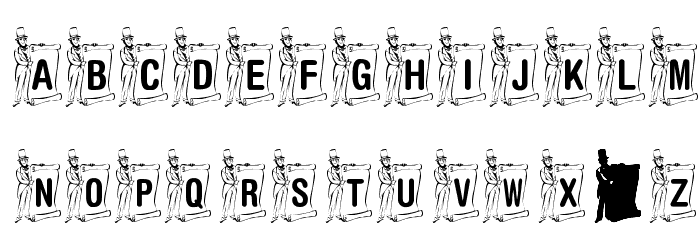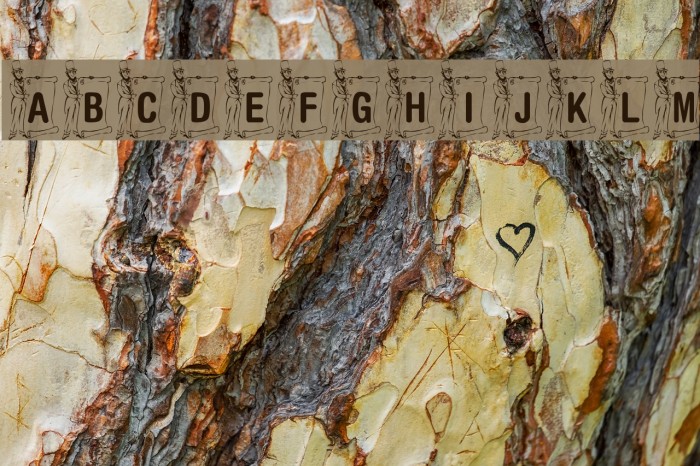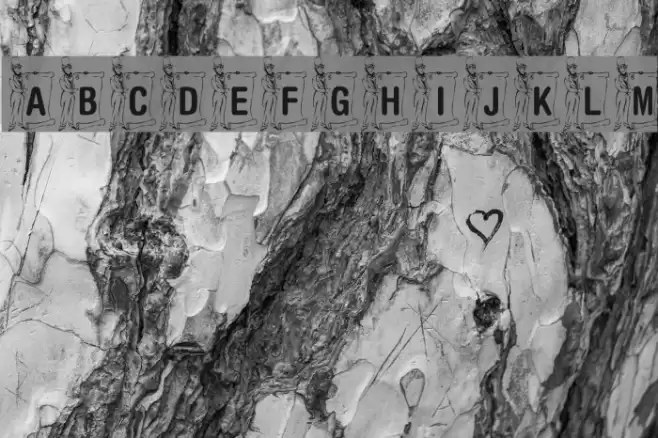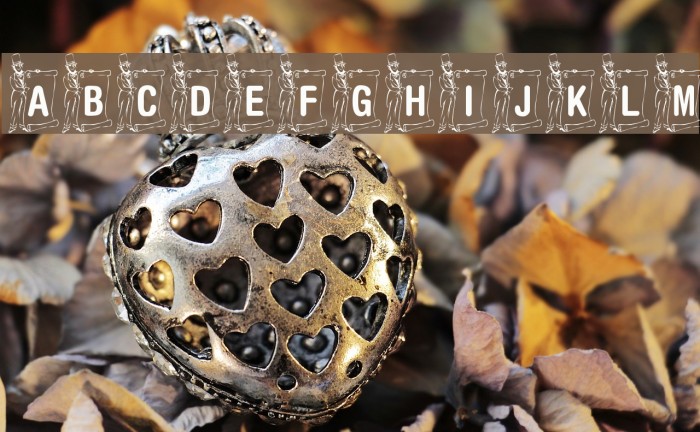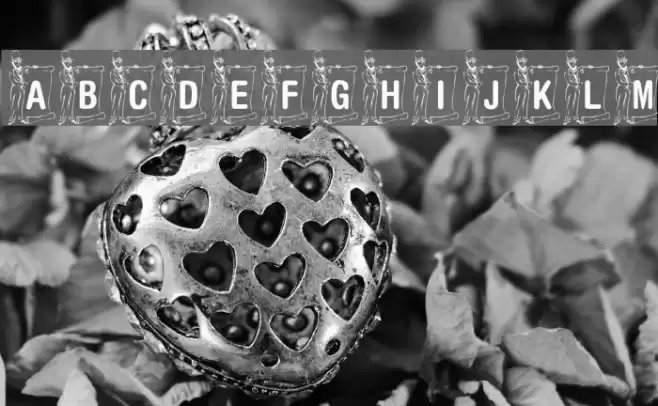
KR Lincoln Font
✎ Retro
| カテゴリ | Retro |
| 用途 | Logos, Headlines, Decorative text |
| おすすめプロジェクト | Perfect for historical-themed posters, vintage book covers, theatrical programs, or any project needing a classical touch. |